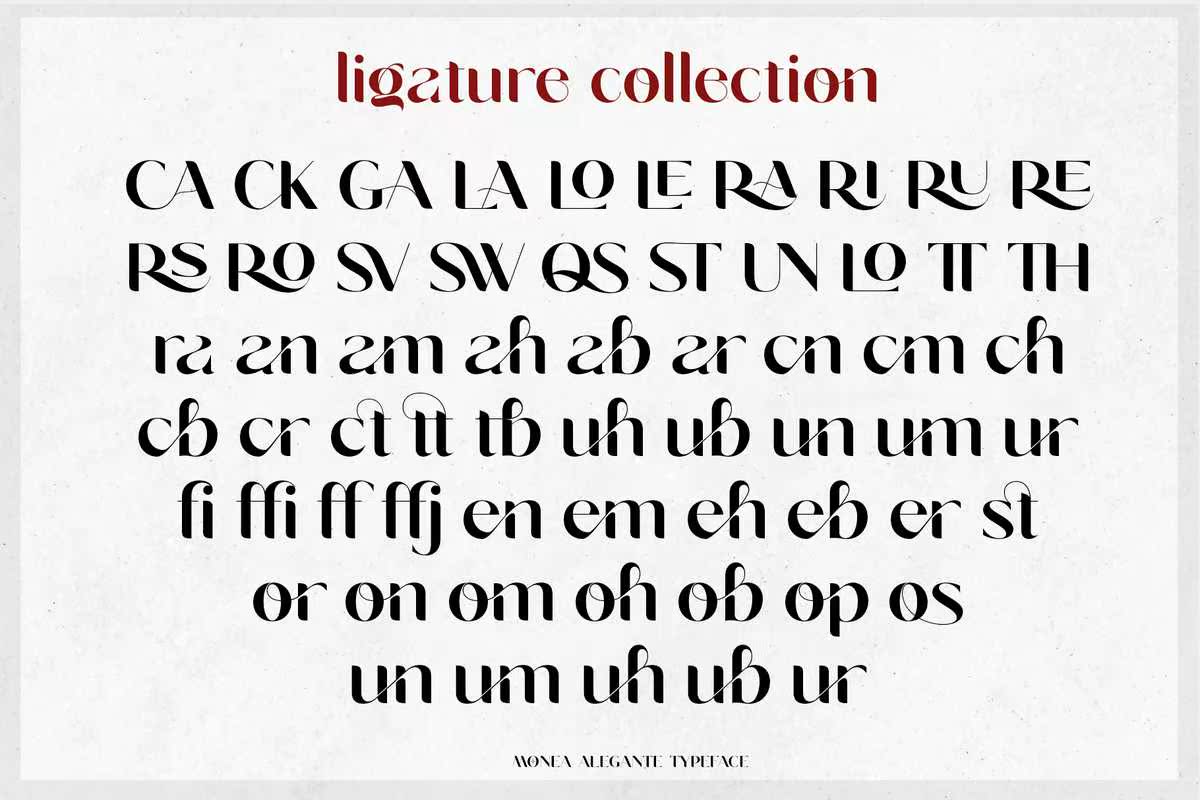
Monea Legante是一款具有美丽的装饰、特殊的可选字体、装饰和多语言支持的全新简约现代维护字体。它具有多种功能,适用于大型和小型产品。适用于品牌项目、标志设计、服装品牌、产品包装、杂志标题、,或简单的文本覆盖在任何背景图像上。功能:5个字体,包括大写字体和大写字体样式替换和连字字符和标点符号格式文件:TTF、OTF、WebMultipleLanguages支持MoneALeganties可折叠的最小字体和现代维护字体,具有漂亮的调节、特殊可选字体的色调,装饰和多语言支持。它具有多种功能,适用于大尺寸和小尺寸。非常适用于品牌项目、标志设计、服装品牌、产品包装、杂志标题或简单的文本,覆盖在任何背景图像上。功能:5字体包括大写和大写样式替换和连字符号和标点符号格式文件:TTF、OTF、,支持WebMultipleLanguages